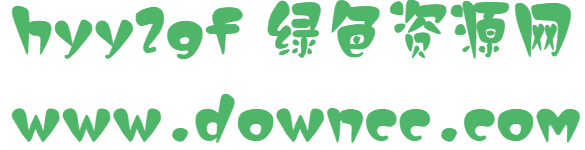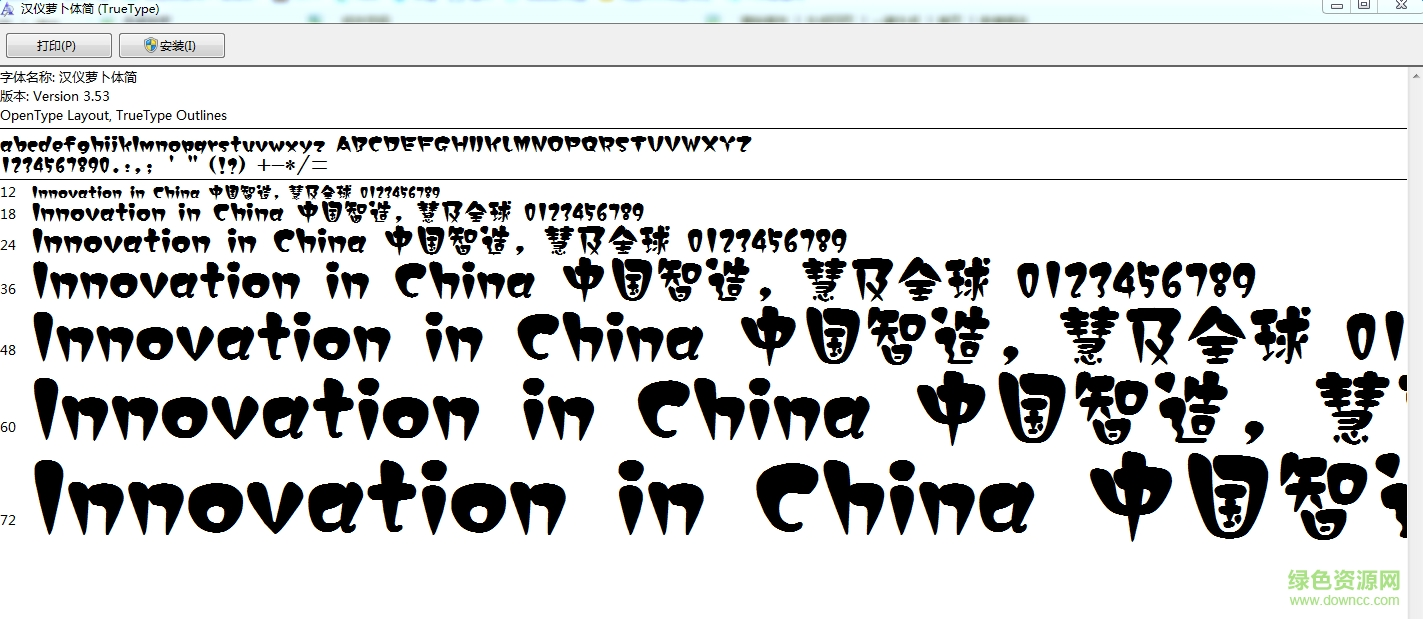
hyy2gf字體就是漢儀蘿卜體,該字體字如其名,就像蘿卜一樣上面粗下面細(xì),天真浪漫又萌又酷,可用作兒童主題的海報(bào)和讀物設(shè)計(jì)或是裝飾字體,喜歡個(gè)性字體的小伙伴快來下載吧!
裝飾字體是在基本字形的基礎(chǔ)進(jìn)行裝飾、變化加工而成的。它的特征是在一定程度上擺脫了印刷字體的字形和筆劃的約束,根據(jù)品牌或企業(yè)經(jīng)營性質(zhì)的需要進(jìn)行設(shè)計(jì),達(dá)到加強(qiáng)文字的精神含義和富于感染力的目的。
筆畫粗壯活潑,構(gòu)思新穎,風(fēng)格獨(dú)特。整體結(jié)構(gòu)為上寬下窄,主要筆畫上邊寬大粗壯,下邊由粗漸小、漸細(xì),似籮卜形狀。具有醒目,突出的視覺效果!